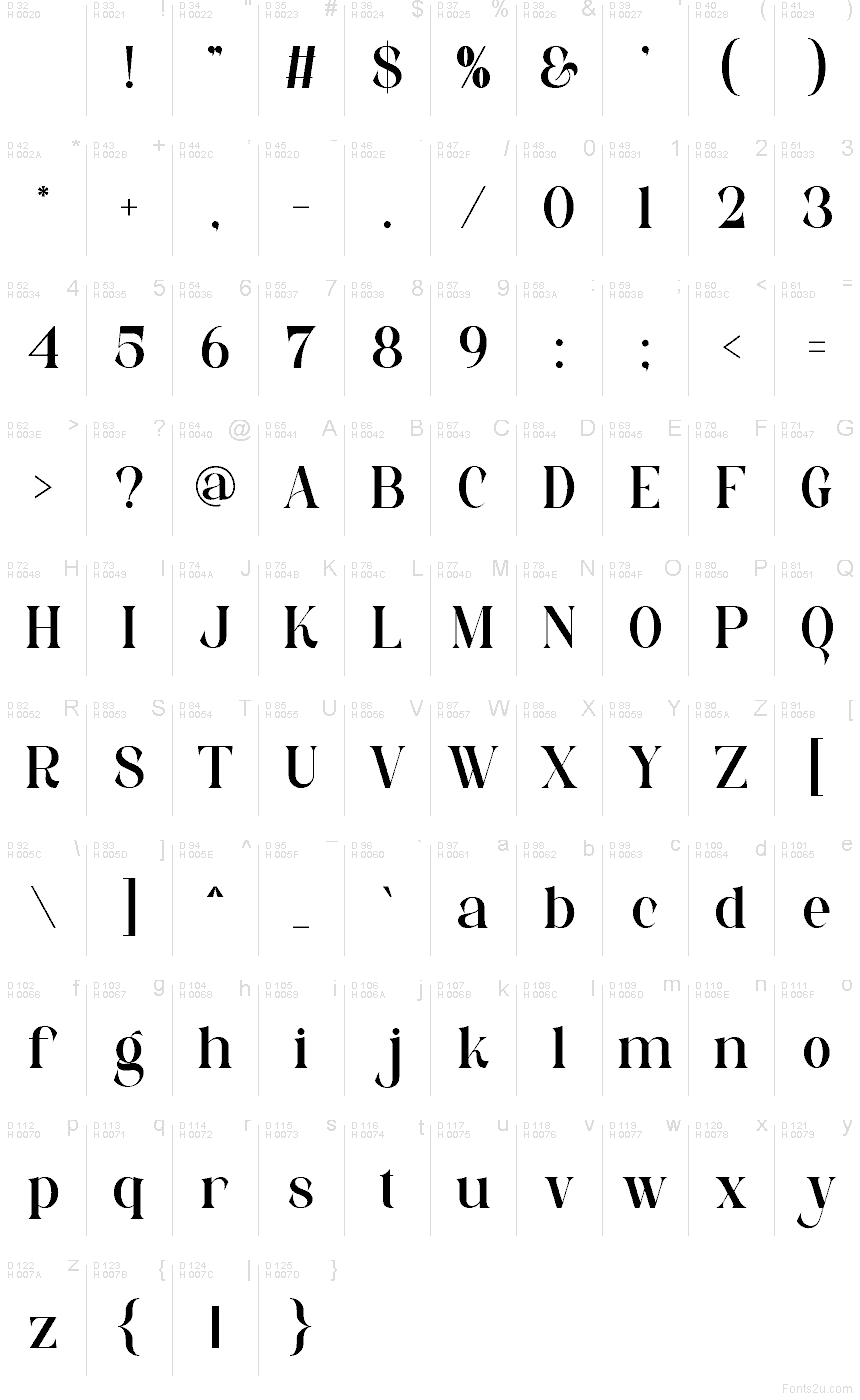
Arseky
Arseky di Ermedia Studio è un carattere con grazie gratuito e ad alto contrasto, contraddistinto da proporzioni slanciate e un'impronta sartoriale d'alta moda. Le sue forme ampie e arrotondate passano bruscamente a tratti sottilissimi, e diverse lettere si allungano in curve affusolate che conferiscono alla composizione un aspetto elegante e deliberatamente teatrale.
La copertina di una rivista di moda è il suo contesto ideale, ma anche il packaging di lusso e il branding per il settore beauty si adattano perfettamente alle sue raffinate forme verticali e alle estreme variazioni di spessore. Su manifesti per eventi e insegne di boutique, le ampie curve possono diventare parte di un monogramma o di un emblema decorativo, invece di limitarsi a fungere da semplice testo all'interno di un impaginato editoriale o di un marchio per vetrina.